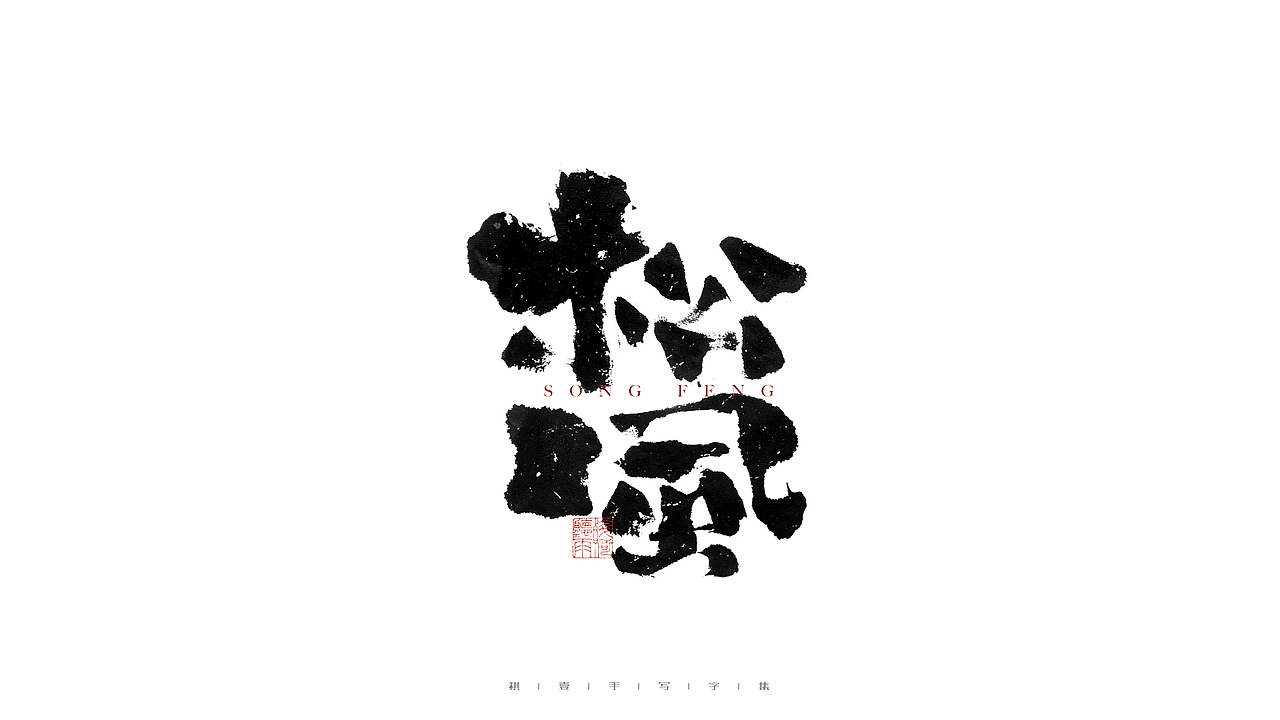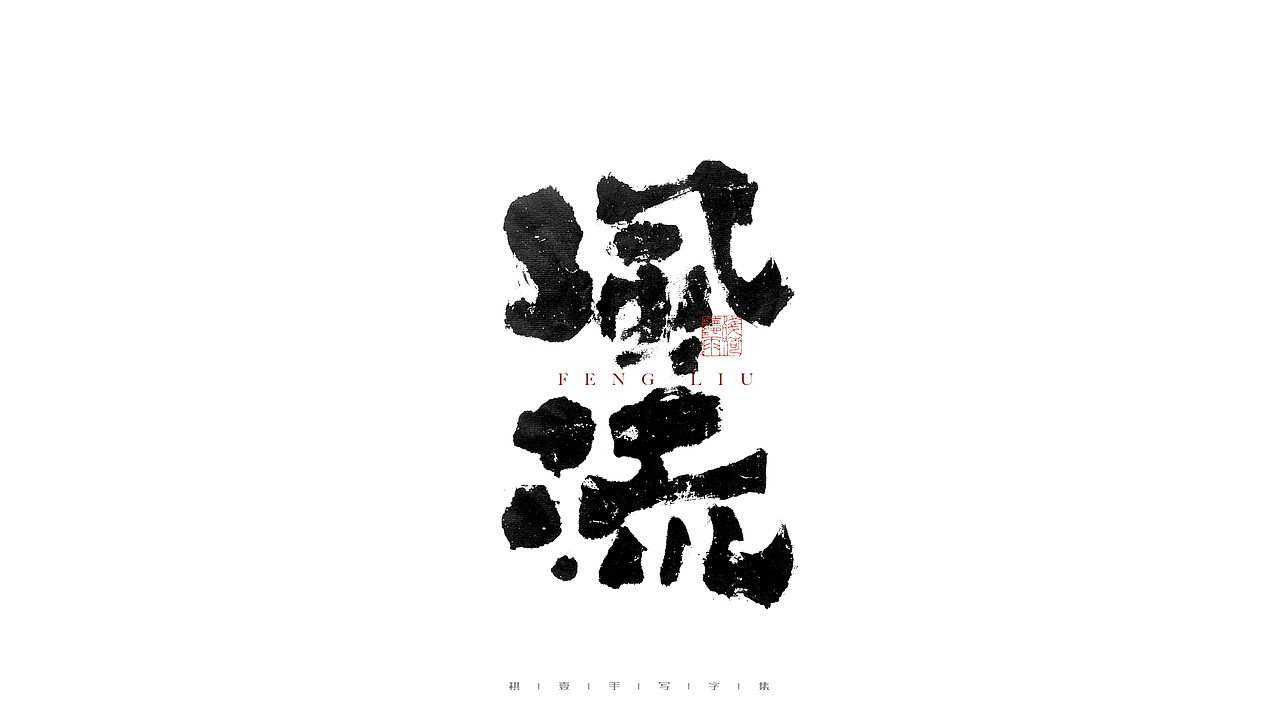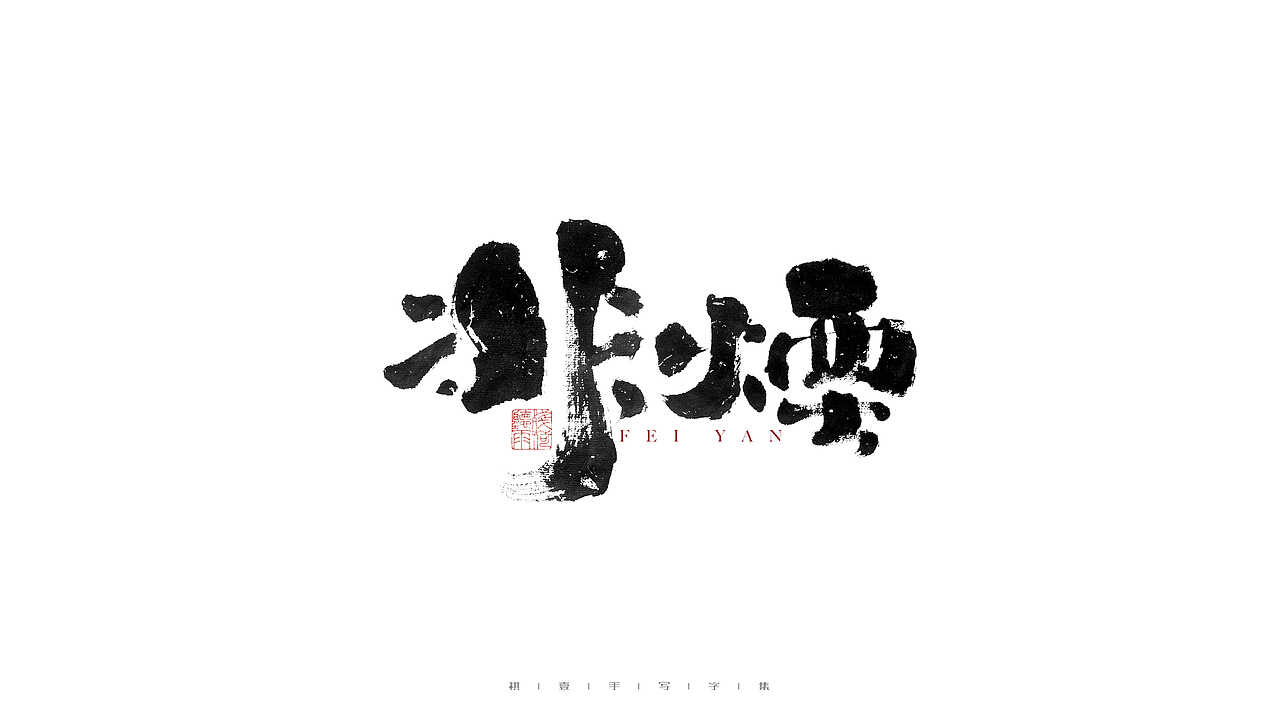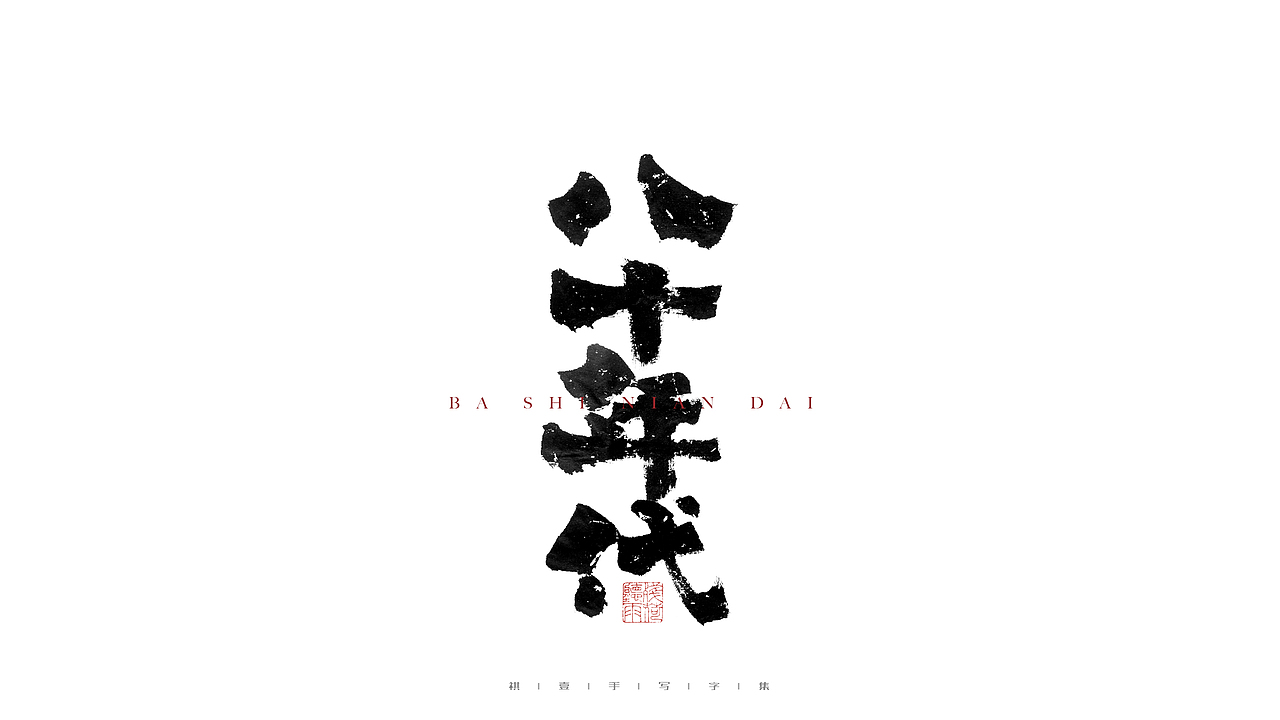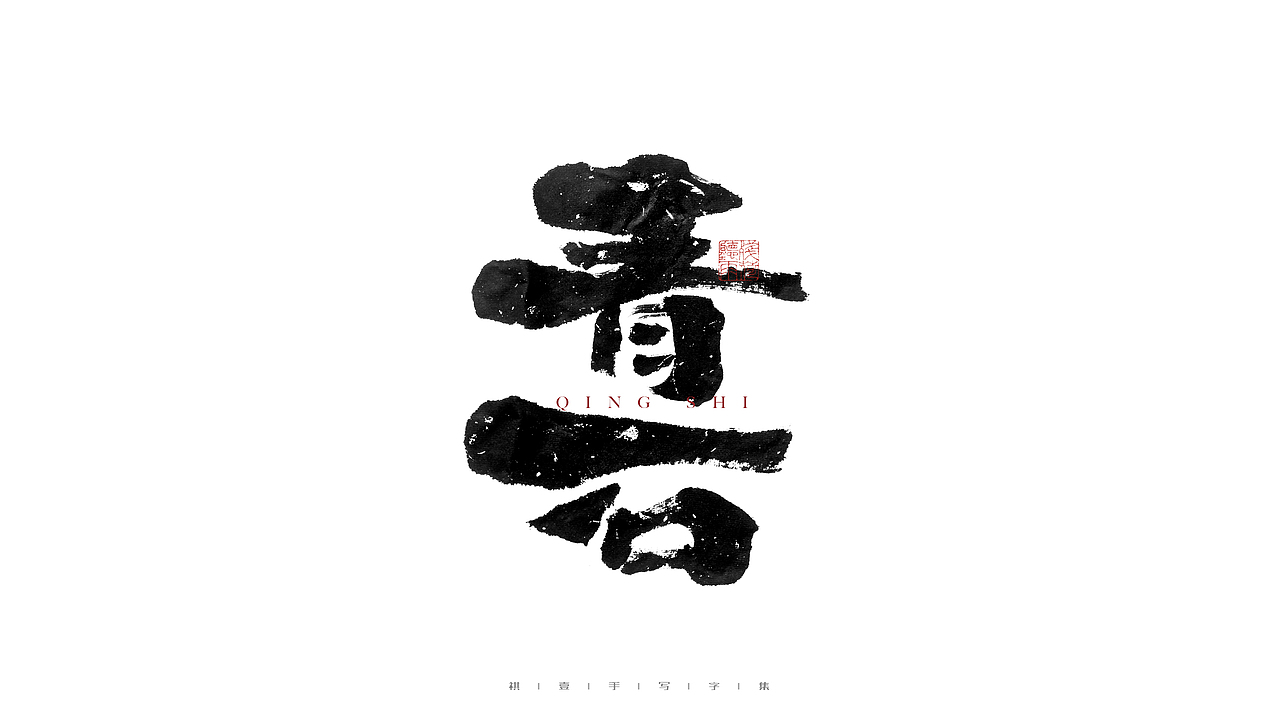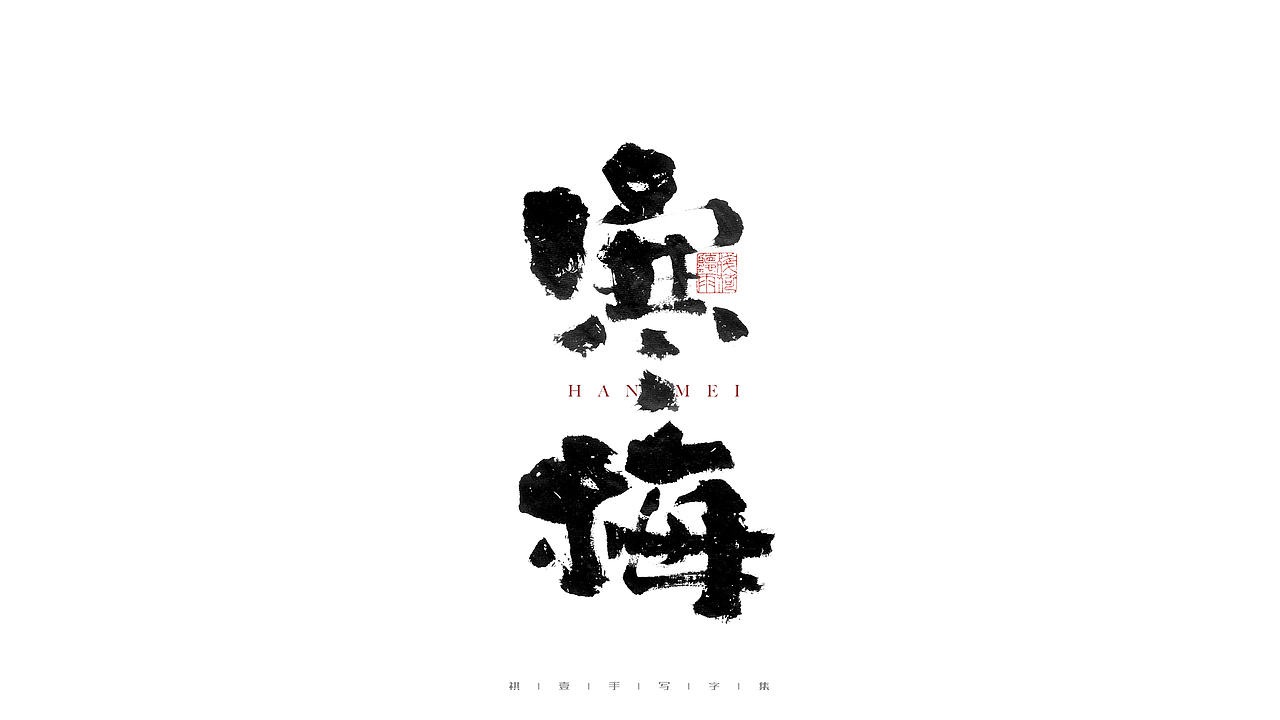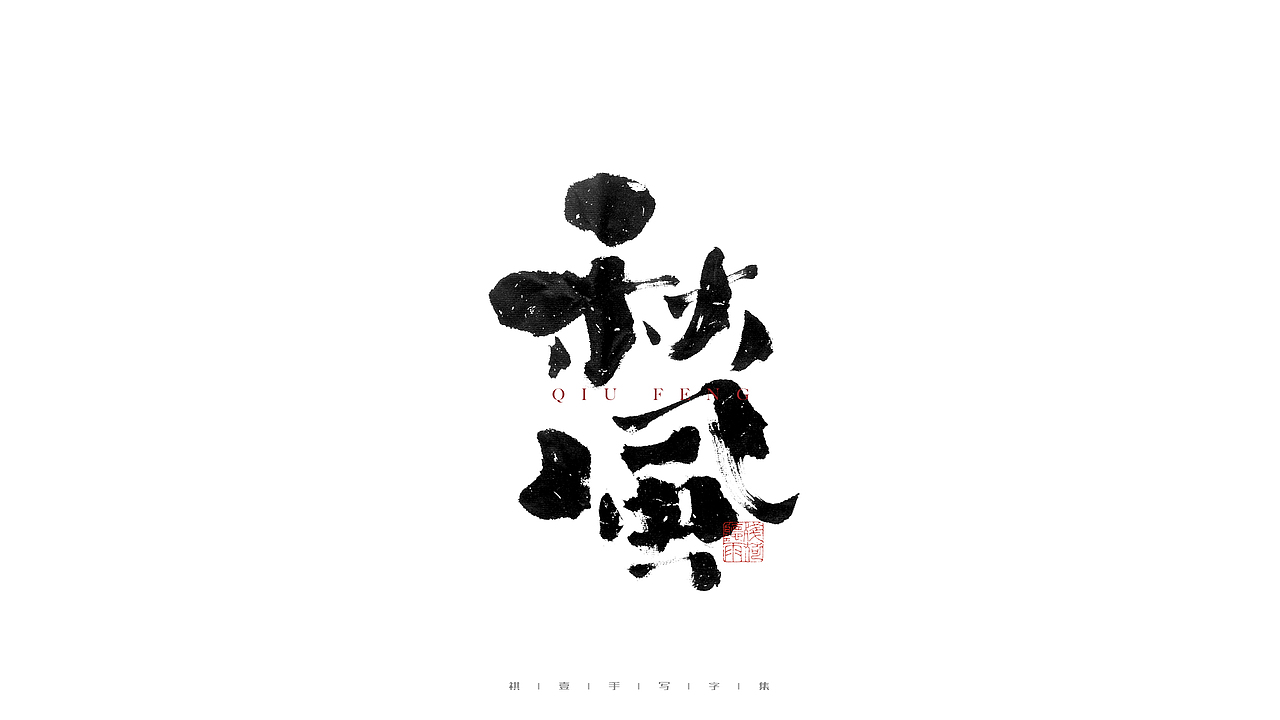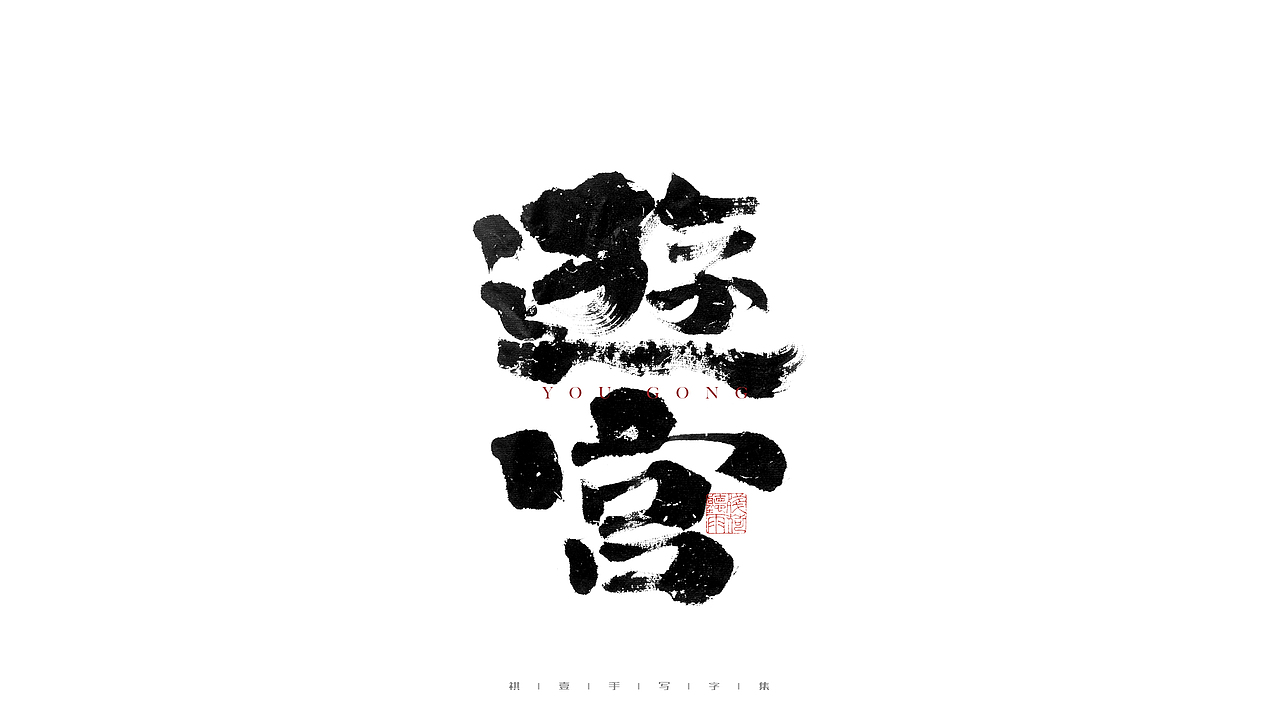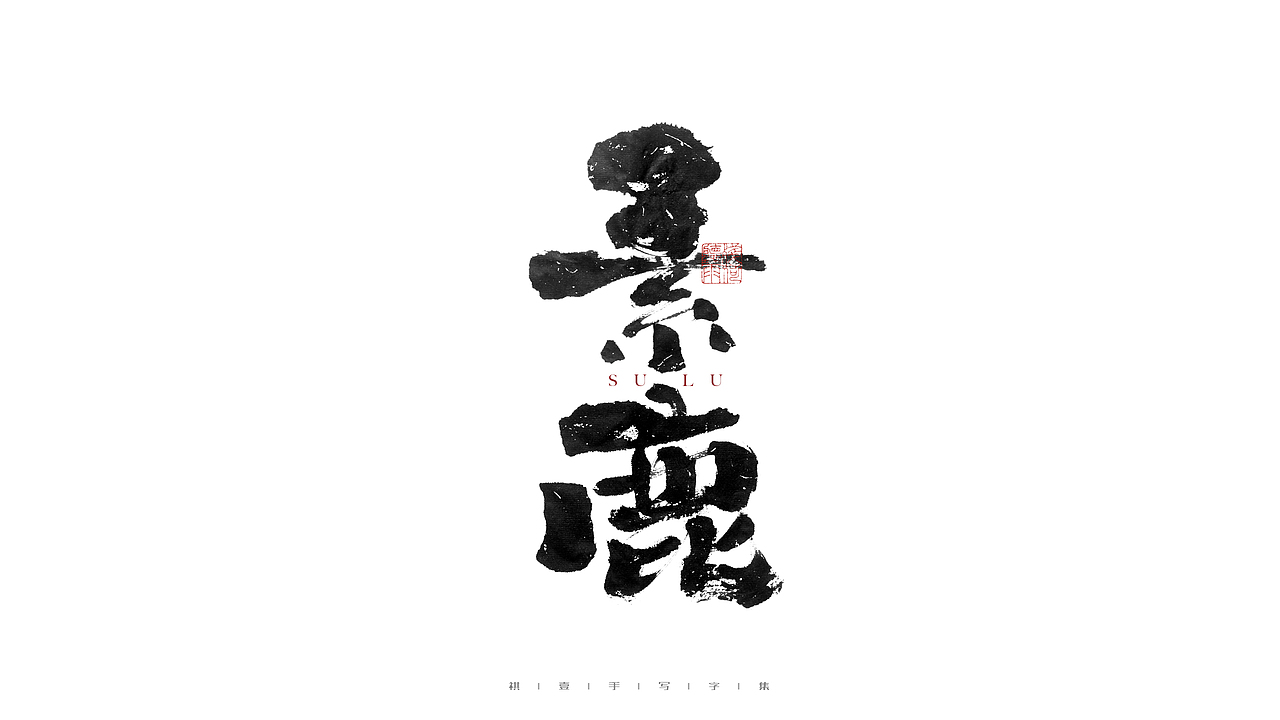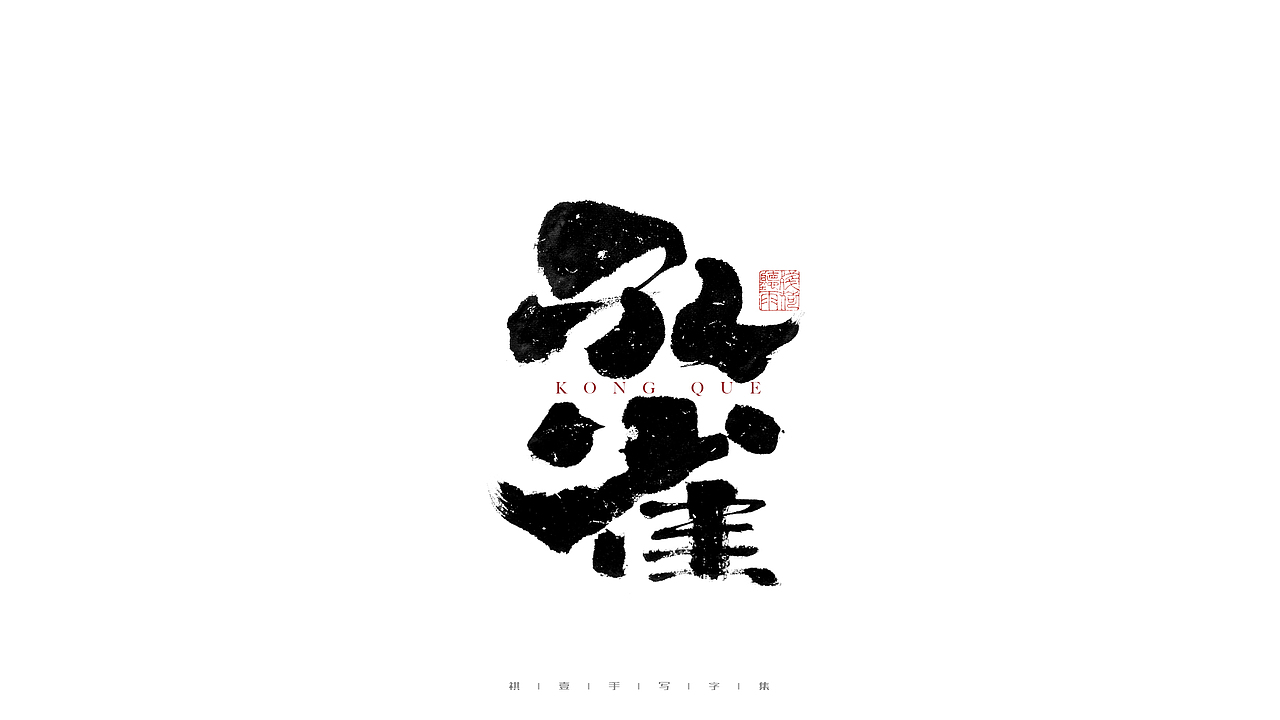
自言字语 —— 一组手写毛笔字(图ZMjgzNzc1OTg0) - 字体/字形 - 站酷设计师祺壹原创素材 - 站酷ZCOOL
自言字语 —— 一组手写毛笔字(图ZMjgzNzc1OTA4) - 字体/字形 - 站酷设计师祺壹原创素材 - 站酷ZCOOL
自言字语 —— 一组手写毛笔字(图ZMjgzNzc1OTA0) - 字体/字形 - 站酷设计师祺壹原创素材 - 站酷ZCOOL
自言字语 —— 一组手写毛笔字(图ZMjgzNzc1OTMy) - 字体/字形 - 站酷设计师祺壹原创素材 - 站酷ZCOOL
自言字语 —— 一组手写毛笔字(图ZMjgzNzc2MDE2) - 字体/字形 - 站酷设计师祺壹原创素材 - 站酷ZCOOL
自言字语 —— 一组手写毛笔字(图ZMjgzNzc2MDAw) - 字体/字形 - 站酷设计师祺壹原创素材 - 站酷ZCOOL
自言字语 —— 一组手写毛笔字(图ZMjgzNzc1OTY0) - 字体/字形 - 站酷设计师祺壹原创素材 - 站酷ZCOOL
自言字语 —— 一组手写毛笔字(图ZMjgzNzc1OTky) - 字体/字形 - 站酷设计师祺壹原创素材 - 站酷ZCOOL
自言字语 —— 一组手写毛笔字(图ZMjgzNzc2MDIw) - 字体/字形 - 站酷设计师祺壹原创素材 - 站酷ZCOOL
自言字语 —— 一组手写毛笔字(图ZMjgzNzc1OTQ4) - 字体/字形 - 站酷设计师祺壹原创素材 - 站酷ZCOOL
自言字语 —— 一组手写毛笔字(图ZMjgzNzc2MDI0) - 字体/字形 - 站酷设计师祺壹原创素材 - 站酷ZCOOL
自言字语 —— 一组手写毛笔字(图ZMjgzNzc1OTYw) - 字体/字形 - 站酷设计师祺壹原创素材 - 站酷ZCOOL
自言字语 —— 一组手写毛笔字(图ZMjgzNzc1OTIw) - 字体/字形 - 站酷设计师祺壹原创素材 - 站酷ZCOOL
自言字语 —— 一组手写毛笔字(图ZMjgzNzc1OTI4) - 字体/字形 - 站酷设计师祺壹原创素材 - 站酷ZCOOL
自言字语 —— 一组手写毛笔字(图ZMjgzNzc1OTEy) - 字体/字形 - 站酷设计师祺壹原创素材 - 站酷ZCOOL
自言字语 —— 一组手写毛笔字(图ZMjgzNzc1OTk2) - 字体/字形 - 站酷设计师祺壹原创素材 - 站酷ZCOOL
自言字语 —— 一组手写毛笔字(图ZMjgzNzc2MDA0) - 字体/字形 - 站酷设计师祺壹原创素材 - 站酷ZCOOL
自言字语 —— 一组手写毛笔字(图ZMjgzNzc1OTc2) - 字体/字形 - 站酷设计师祺壹原创素材 - 站酷ZCOOL
自言字语 —— 一组手写毛笔字(图ZMjgzNzc1OTE2) - 字体/字形 - 站酷设计师祺壹原创素材 - 站酷ZCOOL
自言字语 —— 一组手写毛笔字(图ZMjgzNzc1OTI0) - 字体/字形 - 站酷设计师祺壹原创素材 - 站酷ZCOOL
自言字语 —— 一组手写毛笔字(图ZMjgzNzc1OTUy) - 字体/字形 - 站酷设计师祺壹原创素材 - 站酷ZCOOL
自言字语 —— 一组手写毛笔字(图ZMjgzNzc1OTcy) - 字体/字形 - 站酷设计师祺壹原创素材 - 站酷ZCOOL
自言字语 —— 一组手写毛笔字(图ZMjgzNzc2MDA4) - 字体/字形 - 站酷设计师祺壹原创素材 - 站酷ZCOOL
自言字语 —— 一组手写毛笔字(图ZMjgzNzc1OTY4) - 字体/字形 - 站酷设计师祺壹原创素材 - 站酷ZCOOL
自言字语 —— 一组手写毛笔字(图ZMjgzNzc1OTg4) - 字体/字形 - 站酷设计师祺壹原创素材 - 站酷ZCOOL
自言字语 —— 一组手写毛笔字(图ZMjgzNzc2MDEy) - 字体/字形 - 站酷设计师祺壹原创素材 - 站酷ZCOOL
自言字语 —— 一组手写毛笔字(图ZMjgzNzc1OTM2) - 字体/字形 - 站酷设计师祺壹原创素材 - 站酷ZCOOL
自言字语 —— 一组手写毛笔字(图ZMjgzNzc1OTQw) - 字体/字形 - 站酷设计师祺壹原创素材 - 站酷ZCOOL
自言字语 —— 一组手写毛笔字(图ZMjgzNzc1OTQ0) - 字体/字形 - 站酷设计师祺壹原创素材 - 站酷ZCOOL
自言字语 —— 一组手写毛笔字(图ZMjgzNzc1OTU2) - 字体/字形 - 站酷设计师祺壹原创素材 - 站酷ZCOOL
自言字语 —— 一组手写毛笔字(图ZMjgzNzc1OTgw) - 字体/字形 - 站酷设计师祺壹原创素材 - 站酷ZCOOL
自言字语 —— 一组手写毛笔字(图ZMjgzNzc2MDI4) - 字体/字形 - 站酷设计师祺壹原创素材 - 站酷ZCOOL